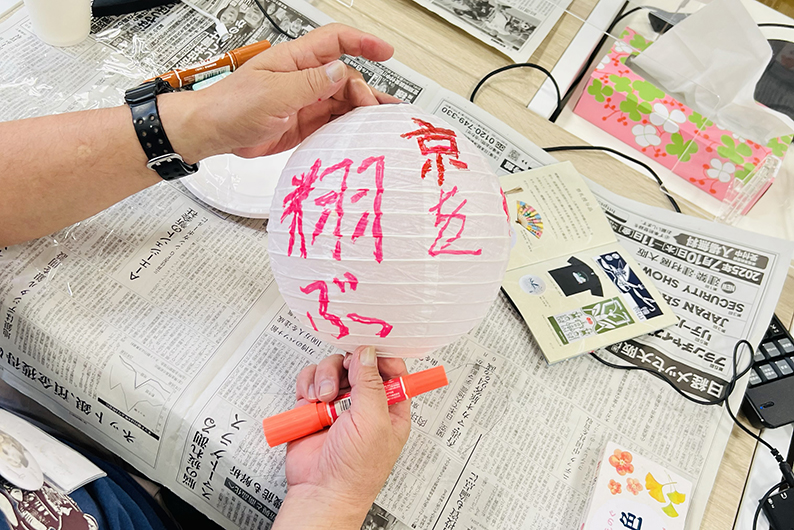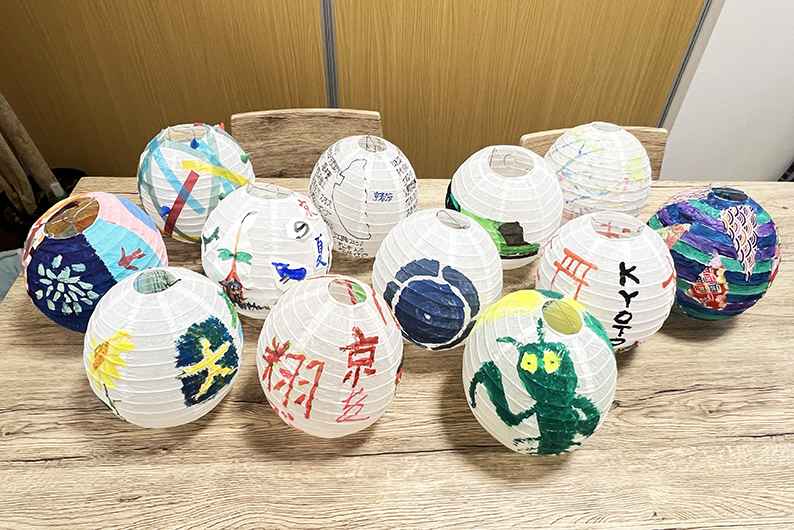
蟷螂山フォント
蟷螂山フォントの背景
京都の中心、四条烏丸にほど近い祇園祭の鉾町・蟷螂山町。
この町に立つ蟷螂山は、南北朝時代の公家・四条隆資の勇敢な姿を、中国の故事「蟷螂の斧(強敵に立ち向かう意)」になぞらえた山鉾です。
大きな力にひるまず、自らの信念を貫くその姿は、時代が移ろっても町衆の心に受け継がれてきました。
支配する者が幾度変わっても、暮らす人々の気概は変わらない。
伝統を守りながらも、新しいものに挑み続ける——その京の町衆の精神はいまもこの町に息づいています。
蟷螂山フォント誕生の思想
強敵に立ち向かう蟷螂の姿は、困難と向き合いながら一歩を踏み出す障害のある方々の挑戦とも重なり、私たちDHCラボがこの取り組みに込めている想いとも深く響き合っています。
さらに蟷螂山は、祇園祭の山鉾の中で唯一、山の上のカマキリがからくりによって動く特別な存在です。
他と同じであることに留まらず、違いを恐れず、独自の表現に挑む。
その意気込みに重ねるように、この場所から新しい試みとして生まれたのが「蟷螂山フォント」です。
蟷螂山フォントに込めた想い
京都・祇園祭の鉾町、蟷螂山町で生まれた蟷螂山フォント。
描かれた一本一本の線には、作者それぞれの想いや時間、感情が込められています。
まっすぐではない線、揺れのある文字、思わず立ち止まってしまうかたち。
そのひとつひとつに、描いた瞬間の気配が残っています。
整いすぎないからこそ、想いが伝わる。読むたびに、こころがふっと近づく文字です。
このフォントは、障害のある方、プロのデザイナー、学生、そして地域の人々が立場を越えて関わり合い、共に創り上げてきました。
蟷螂山フォントのこれから
描くこと、整えること、使われること。
そのすべての工程が、地域と人をつなぐコミュニケーションとなり、新しい表現のかたちを育んでいます。
創作を通して誰かに必要とされ、社会の一員であることを実感する喜びは、次の一歩への原動力となります。蟷螂山フォントは、単なるフォント制作にとどまらず、文字やイラストといった表現を通して、人と地域、社会をつなぐプラットフォームとしての可能性を広げていきます。
フォントに加え、イラストやパターンなど多様な表現を展開し、使う人それぞれの場面で新たな物語が生まれることを目指します。
文字という身近で基本的な意思伝達のツールを起点に、共感と理解が循環する社会へ。
蟷螂山フォントは、地域から未来へと続く、ひらかれた挑戦です。